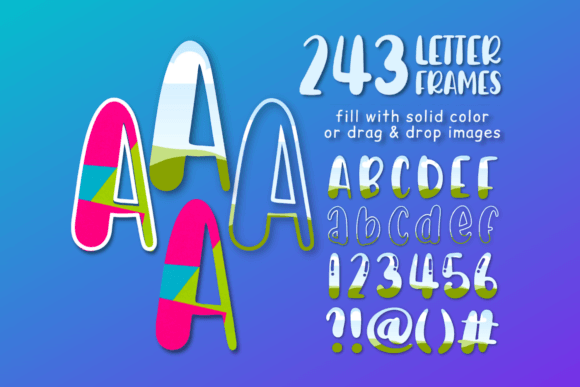
Doodle Letters Bubble Font Canva Frames
أضف لمسة مرحة وإبداعية إلى تصميماتك مع حروف دوودل وفقاعات – إطار كانفا!
هذا المنتج يجمع بين الخطوط البسيطة والمرسومة يدويًا مع الإطارات الفريدة التي تمنح أعمالك أسلوبًا ممتعًا وجذابًا.
• تصميمات مبتكرة: حروف وفقاعات مرسومة يدويًا تضفي حيوية ومرحًا على مشاريعك.
• إطارات كانفا مميزة: تناسب تصميماتك على منصة Canva بسهولة ومرونة.
• جودة عالية: تفاصيل دقيقة وصور واضحة لتناسب الطباعة أو الاستخدام الرقمي.
• قابل للتخصيص: يمكنك تعديل الأحجام والألوان لتتناسب مع أسلوبك الإبداعي.
• يجعل تصميماتك تبرز بأسلوب فريد ومرسوم يدويًا.